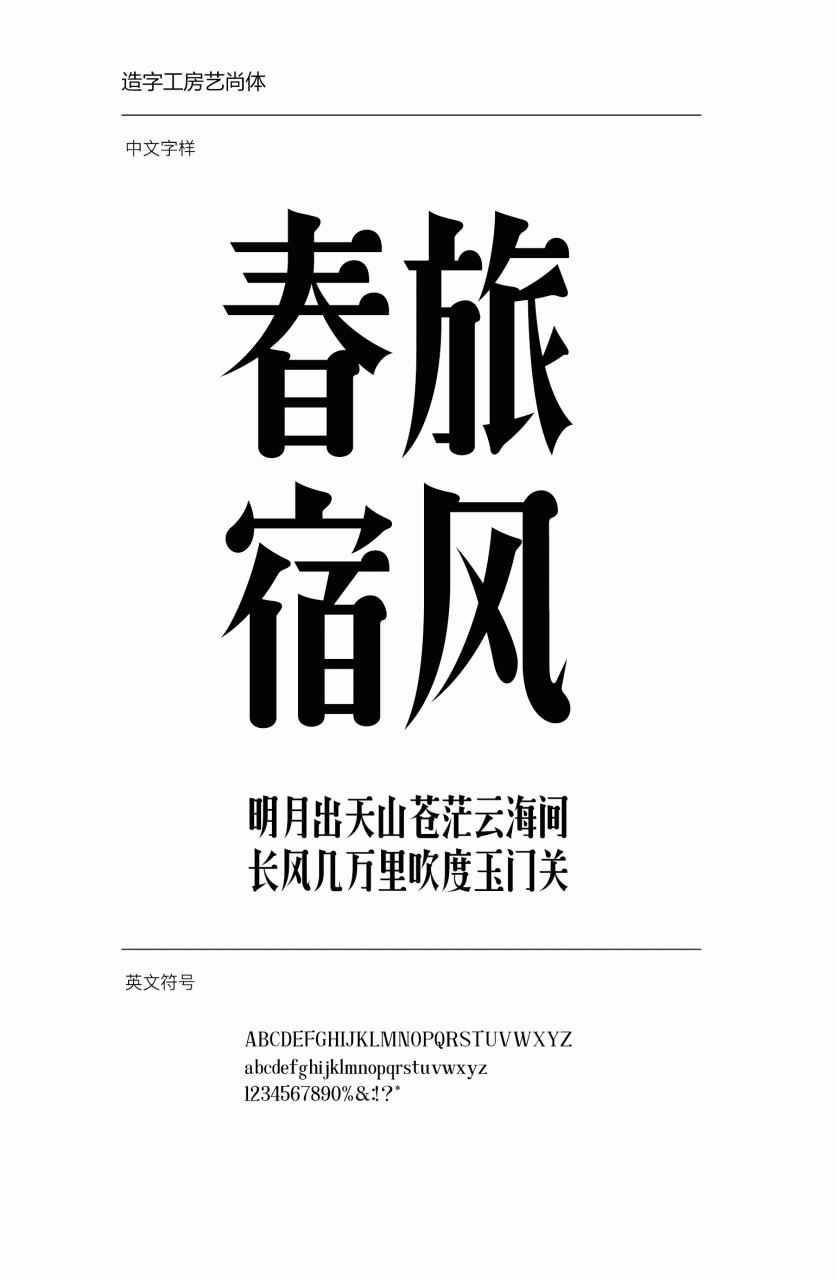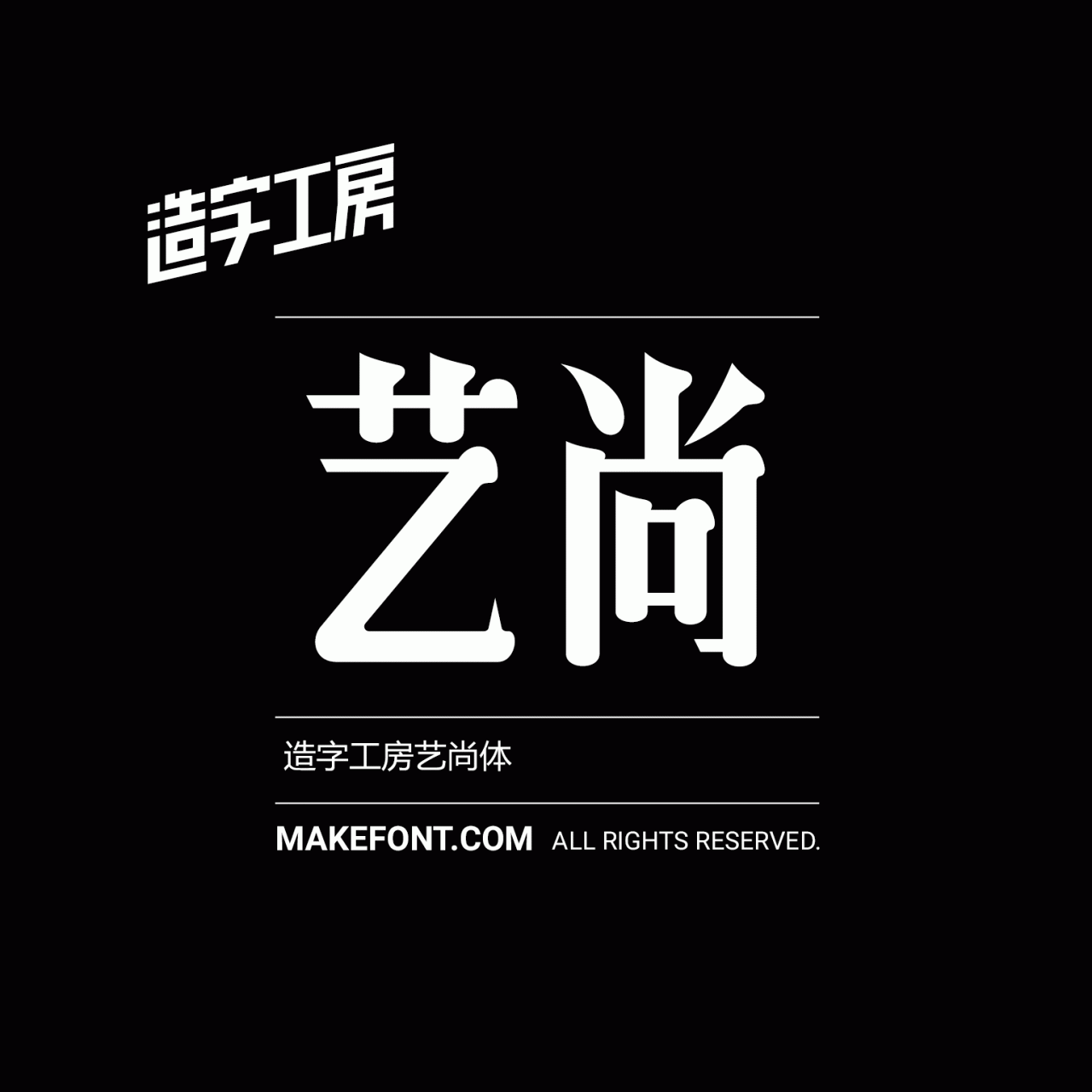
字体简介 造字工房艺尚体以宋体字形结构为特点,纤长有律,瑞丽秀气却又不失稳重大气之感,如玉盘珠女稳而轻佻,文艺范儿十足。适用于大标题及个性品牌设计推广等环境。本字体为简体字库,采用OpenType/CID格式,Adobe-GB1-5编码。基于中华人民共和国GB2312-80字符集标准,另按需添加101个汉字。共收容字数6864CJK汉字,ASCII常用字符100个。 字体下载地址 云下载